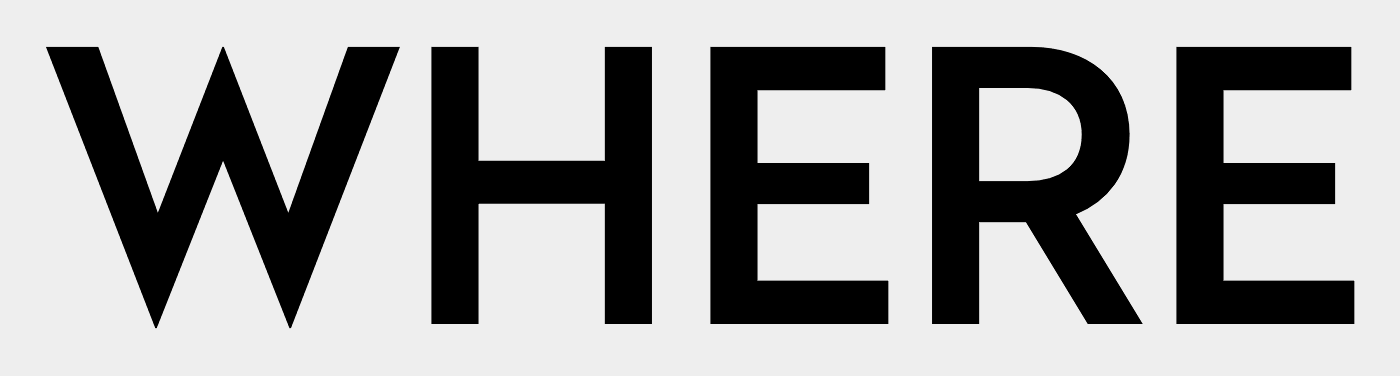
Welche Schriftart könnte das sein?
ich habe hier eine Schriftart gefunden nur leider weiß ich nicht welche das sein könnte :/
ich habe von mir alle durchsucht nur leider finde ich diese nicht :(
Im gesuchten Beispiel sind aber keine Störungen und kein nach oben verschobenes R zu sehen.
Die Radikal Medium könnte nahe kommen …